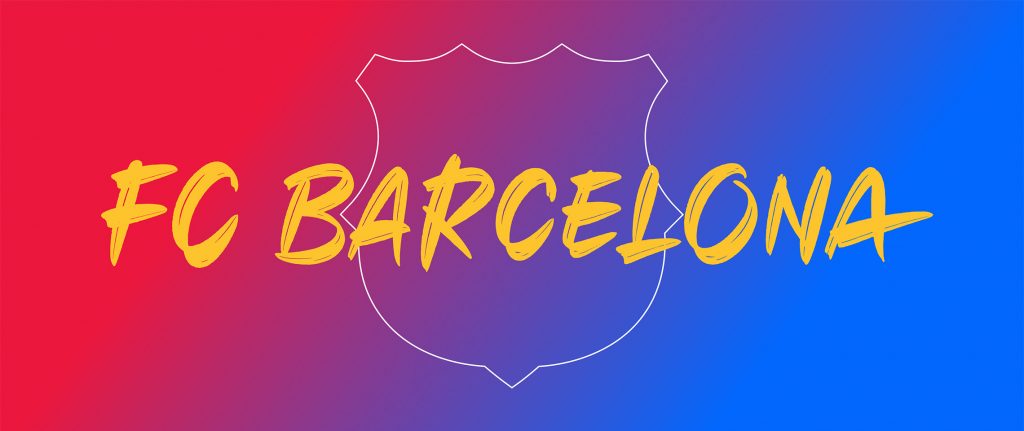
Así es la nueva tipografía del FC Barcelona creada por ArillaType
Se llama FC Barcelona Brush y ha sido realizada por ArillaType para completar el nuevo branding del Barça creado por Summa.
Apenas cuatro años después de su rebranding, el FC Barcelona ha decidido renovar parte de su identidad visual. La renovación de 2018 fue una clara apuesta por el flat design para adaptarse a los medios digitales. El diseño fue realizado por Summa y contó con una nueva tipografía realizada en colaboración entre Summa e Iñigo Jérez. Ahora han decidido sumar con una nueva tipografía que rompe con los estereotipos habituales.